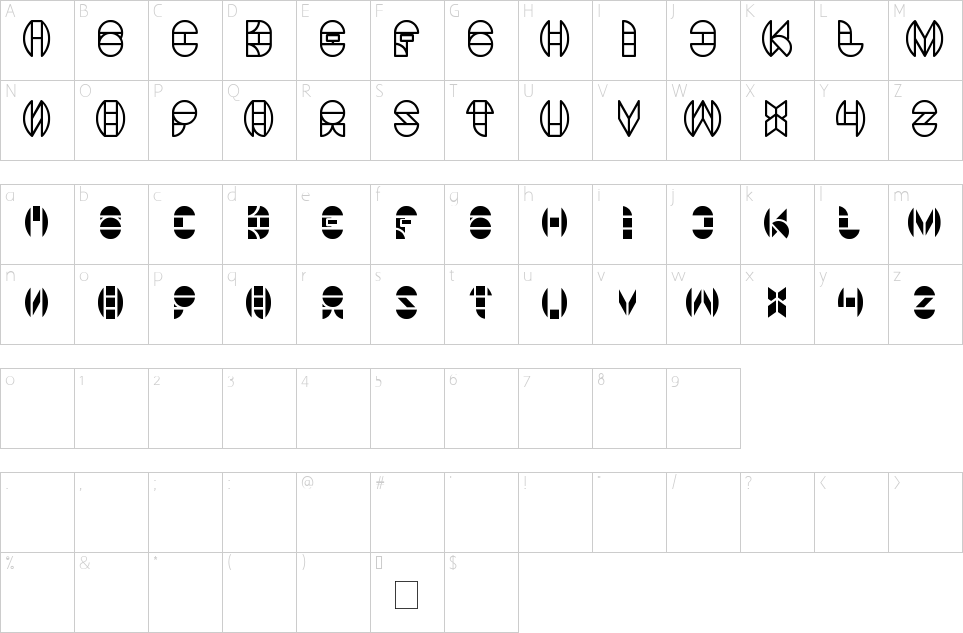
A Dragon Fly é uma elegante e fluida fonte que se destaca com sua disposição curiosa e vibrante. Desenvolvida por weknow, esta delicada fonte oferece um toque de natureza ao seu design gráfico. Seja para adicionar um ar sofisticado a seus projetos digitais ou para dar vida à sua tipografia impressa, Dragon Fly é uma excelente escolha. Com downloads consolidados em mais de 1.964 vezes, não é surpresa que a Dragon Fly tenha se tornado uma fonte favorita entre criadores de design e designers. Se você está procurando por um estilo único que encaixa perfeitamente na sua próxima arte digital ou projeto gráfico, a Dragon Fly é definitivamente um investimento em qualidade.